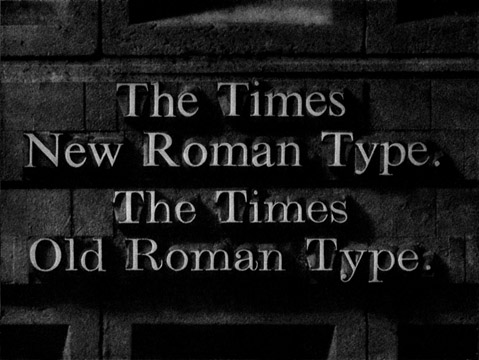
Новый и старый
Times
в металле. Иллюстрация из специального выпуска бюллетеня The Monotype Recorder, посвященного внедрению нового шрифта в газете The Times, 1932 г.